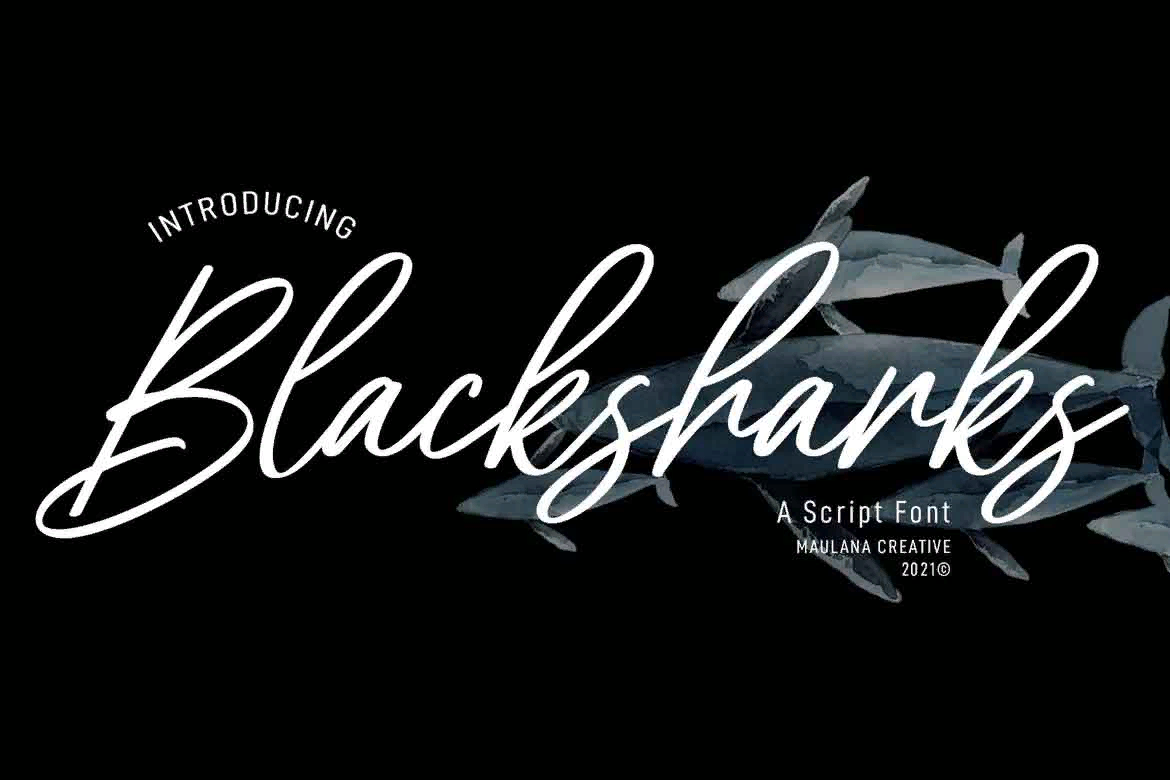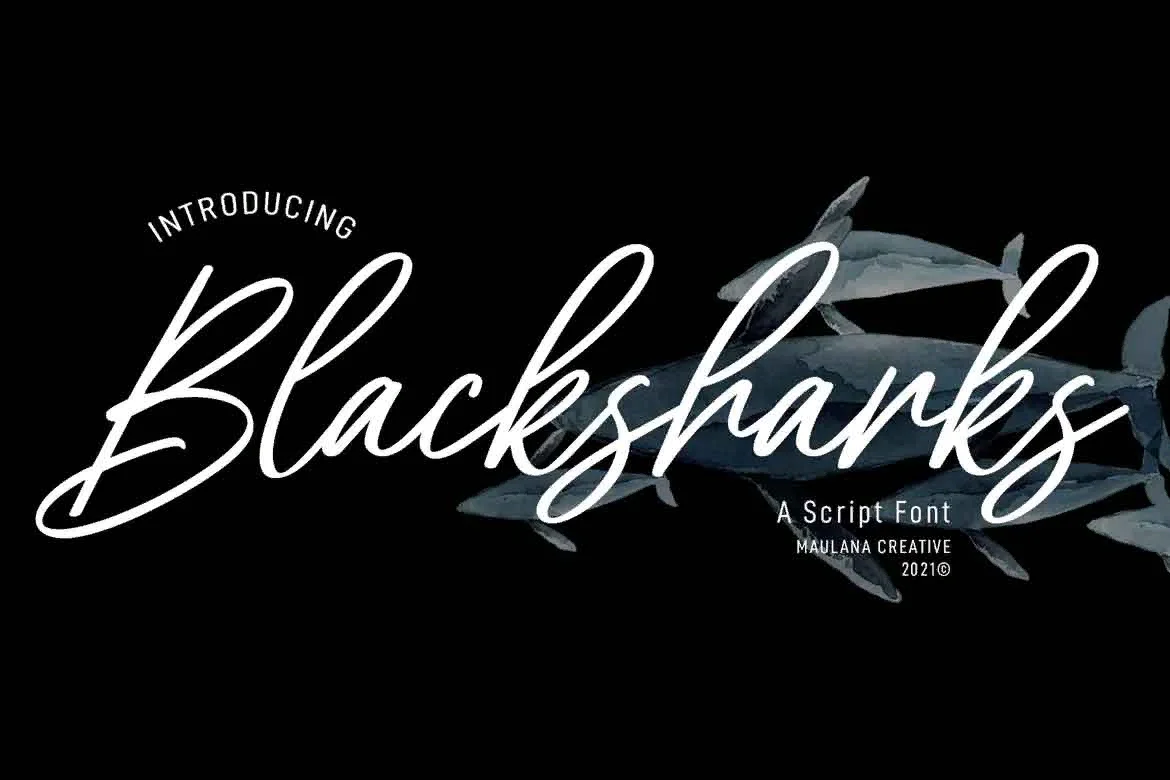
Название: Blacksharks Font (2021)
Blacksharks Script - это непринужденный шрифт с очаровательными, игривыми персонажами, которые словно танцуют вдоль базовой линии.